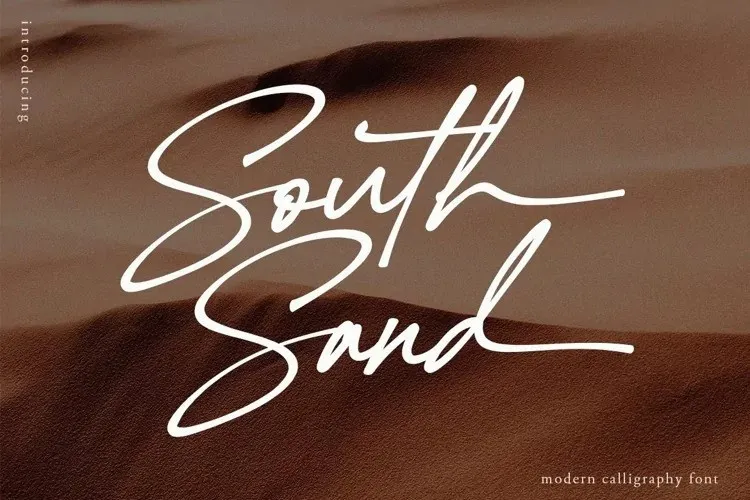
A South Sand Font é uma elegante tipografia feita à mão que se destaca por sua fluida escrita única. Feita para atender às necessidades criativas de designers, este moderno estilo de caligrafia foi desenvolvido com traços naturais obtidos através do uso da folha de papel, permitindo uma aplicação versátil em diferentes projetos como marcas, citações e convites. Esta fonte é perfeitamente adaptada para atender aos mais variados requisitos de design, tornando-a um recurso valioso para qualquer designer profissional ou hobbyista que busque um toque elegante em suas criações. Com uma descrição original cuidadosa feita pela Viswell Studio e disponibilizada pela 99designs, a South Sand Font certamente fará sua marca na cena da tipografia digital.